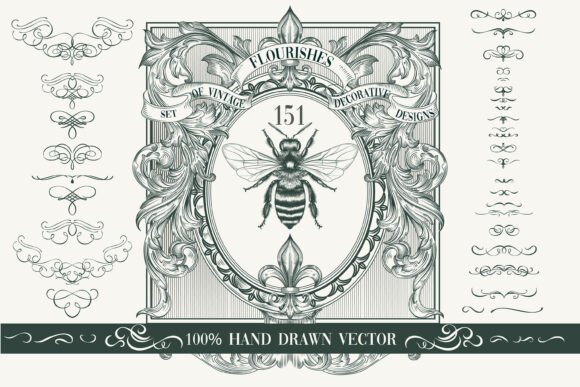
Calligraphic Set of Vintage Flourishes
การค้นหาองค์ประกอบการออกแบบที่เหมาะสมอาจเป็นเรื่องท้าทาย แต่ Calligraphic Set of Vintage Flourishes นำเสนอคอลเลกชันที่โดดเด่นซึ่งช่วยยกระดับงานของคุณได้ทันที
ไม่ว่าคุณจะสร้างผลิตภัณฑ์ POD (Print on Demand) คำเชิญงานแต่งงาน หรือกราฟิกโซเชียลมีเดีย Calligraphic Set of Vintage Flourishes ก็เหมาะสมอย่างยิ่ง